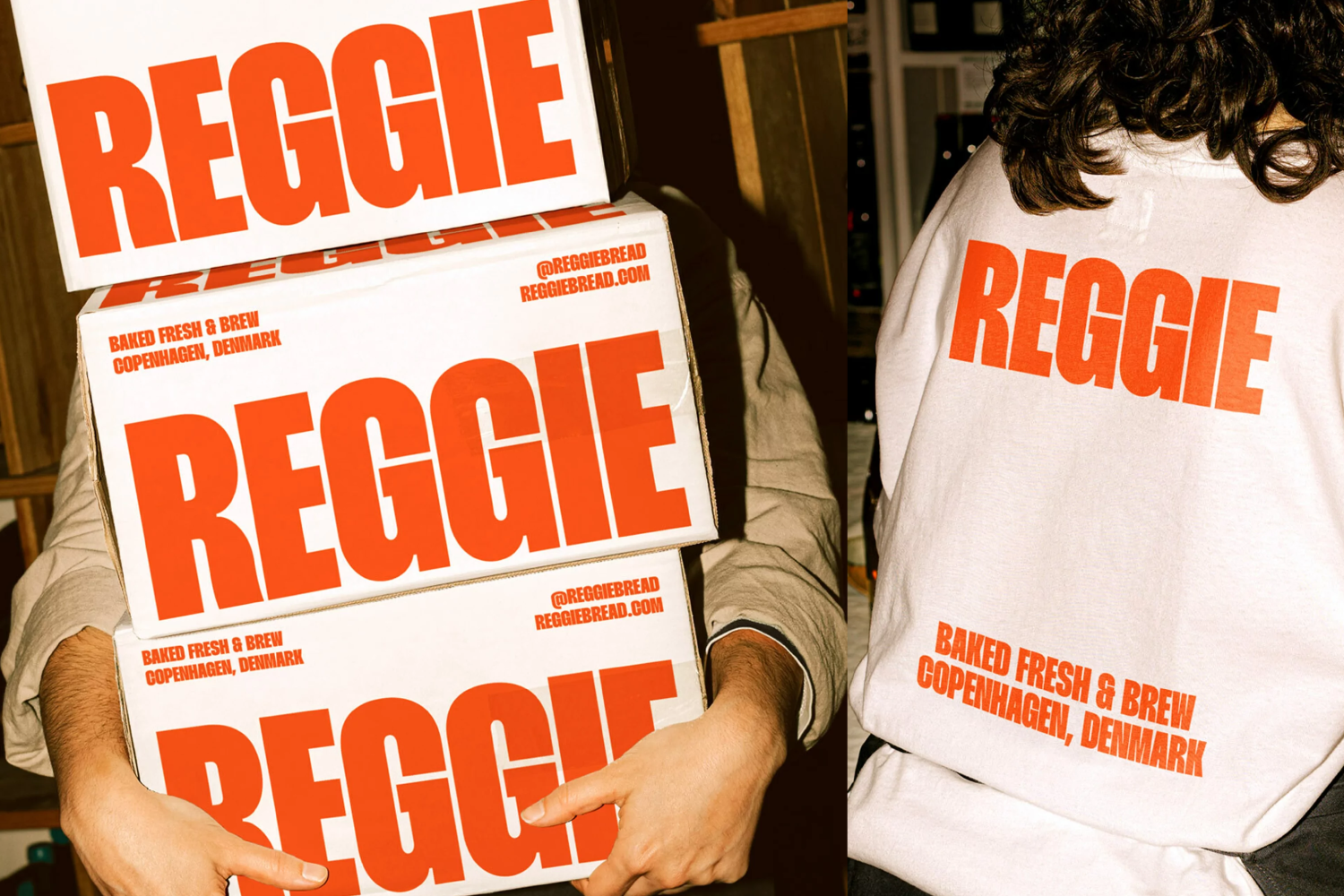
Cada época posee sus propias tendencias estéticas que la definen. Estas tendencias no germinan por generación espontánea. Se manifiestan por la confluencia de una serie de factores entre los que destacan principalmente los avances técnicos que las hacen posibles y las realidades sociales, políticas, económicas y culturales que les dan forma y profundidad.
Si analizamos el presente bajo este prisma, nos daremos cuenta enseguida de que la aceleración de los avances tecnológicos —con la IA a la cabeza— están provocando una auténtica revolución visual. A su vez, desde que comenzó el siglo XXI estamos inmersos en una convulsa actualidad sociopolítica mundial que, grosso modo, lo está poniendo todo patas arriba, y que, lejos de amainar, cada día parece ir a más. Ambas circunstancias interactúan y se retroalimentan; son causa y a la vez efecto la una de la otra.
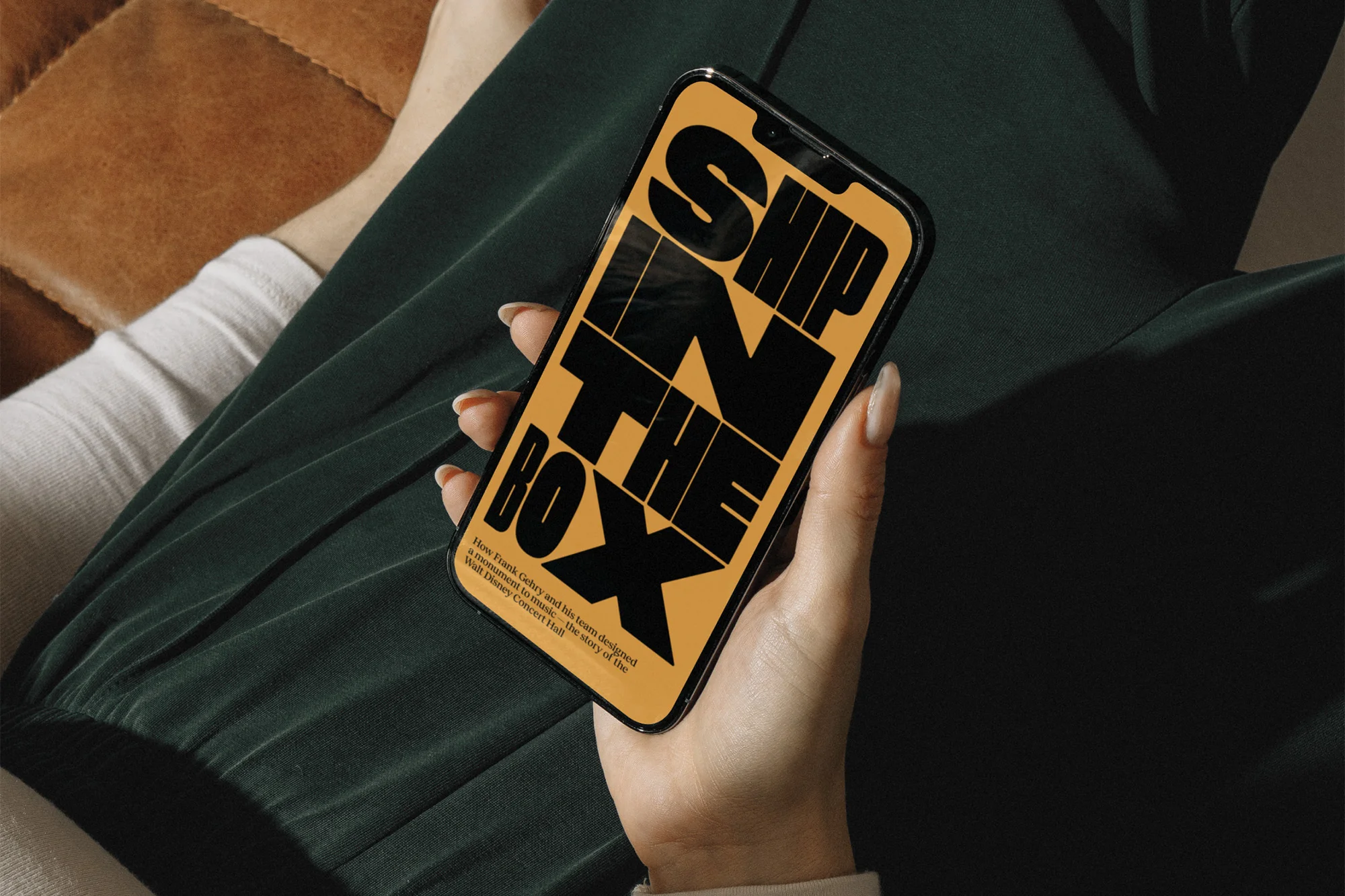
¿Y qué nos dice la tipografía de todo esto?
El diseño gráfico y la tipografía —y el universo de la cultura visual en general— son un reflejo del mundo en el que surgen y en este agitado y salvaje mundo de 2024 es imposible, a mi juicio, destacar una tendencia por encima de las demás, posiblemente como consecuencia de la agitación social. Llevamos años haciendo estos ejercicios de recapitulación y después de este tiempo es posible concluir que la tendencia tipográfica predominante es que no hay tendencia tipográfica predominante.
A lo largo de este artículo, vamos a repasar algunas tendencias, corrientes o movimientos tipográficos que nos parecen significativos y que, bajo nuestro punto de vista, son los que marcan el presente. Como hemos dicho en alguna ocasión anterior, no tenemos afán de exhaustividad, sino que lo que pretendemos no es más que esbozar un retrato tipográfico personal de la actualidad, tal vez como excusa para hacer algo que adoramos: hablar de tipografía.
Tipografías invertebradas
La tipografía solía tener esqueleto. Durante siglos ha sido sinónimo de solidez, de precisión arquitectónica. Pero ya no es así. Las dos dimensiones ya no son lo que eran. Las letras se vuelven blandas y flexibles, son como burbujas que se hinchan, incluso parece que se van a escapar de la pantalla. Lo que antes parecía anatema ahora se hace con descaro: las letras se deforman y no es difícil sospechar que en ello hay rebeldía y un decidido afán por dejar bien claro que, en realidad, no todo está inventado.
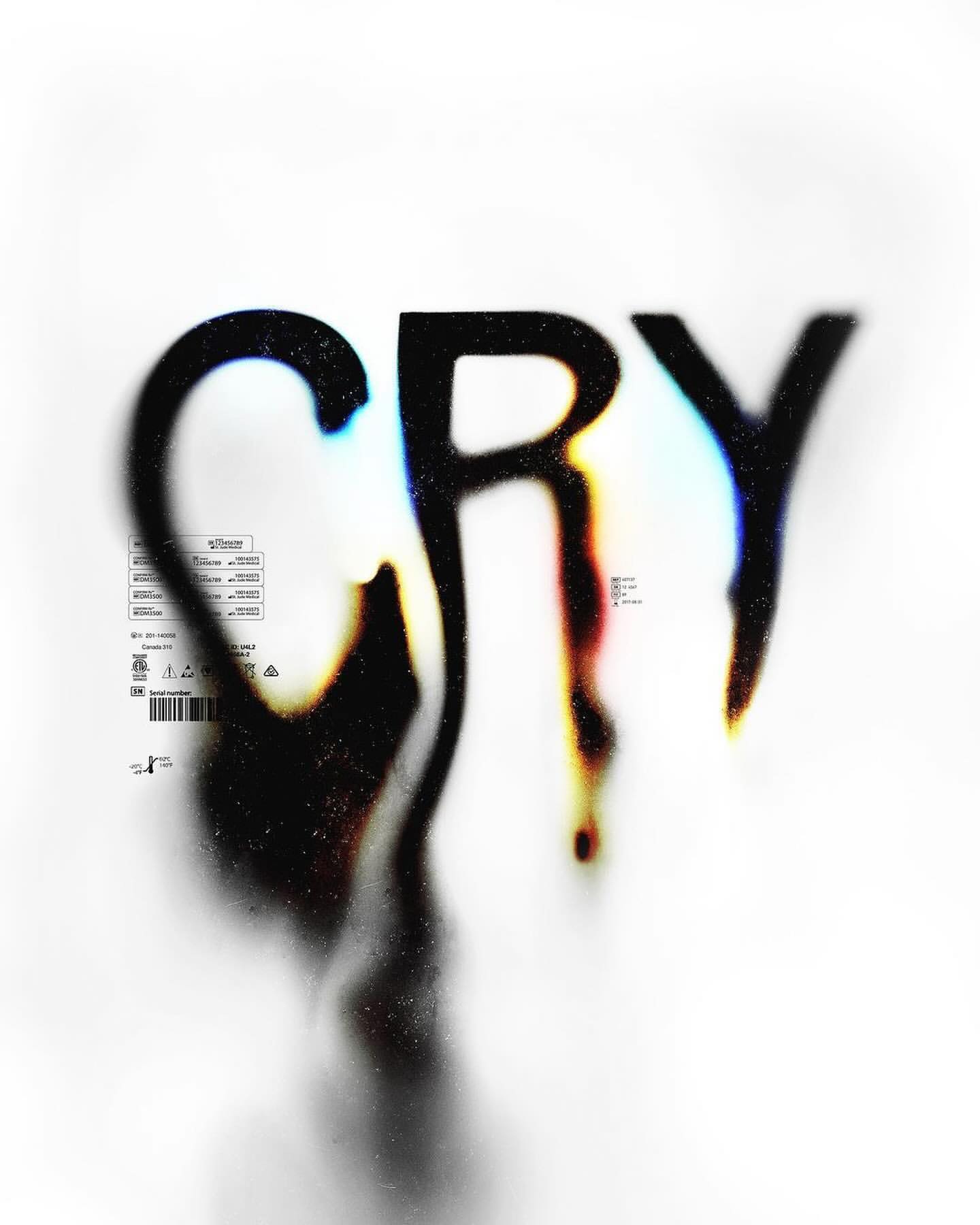
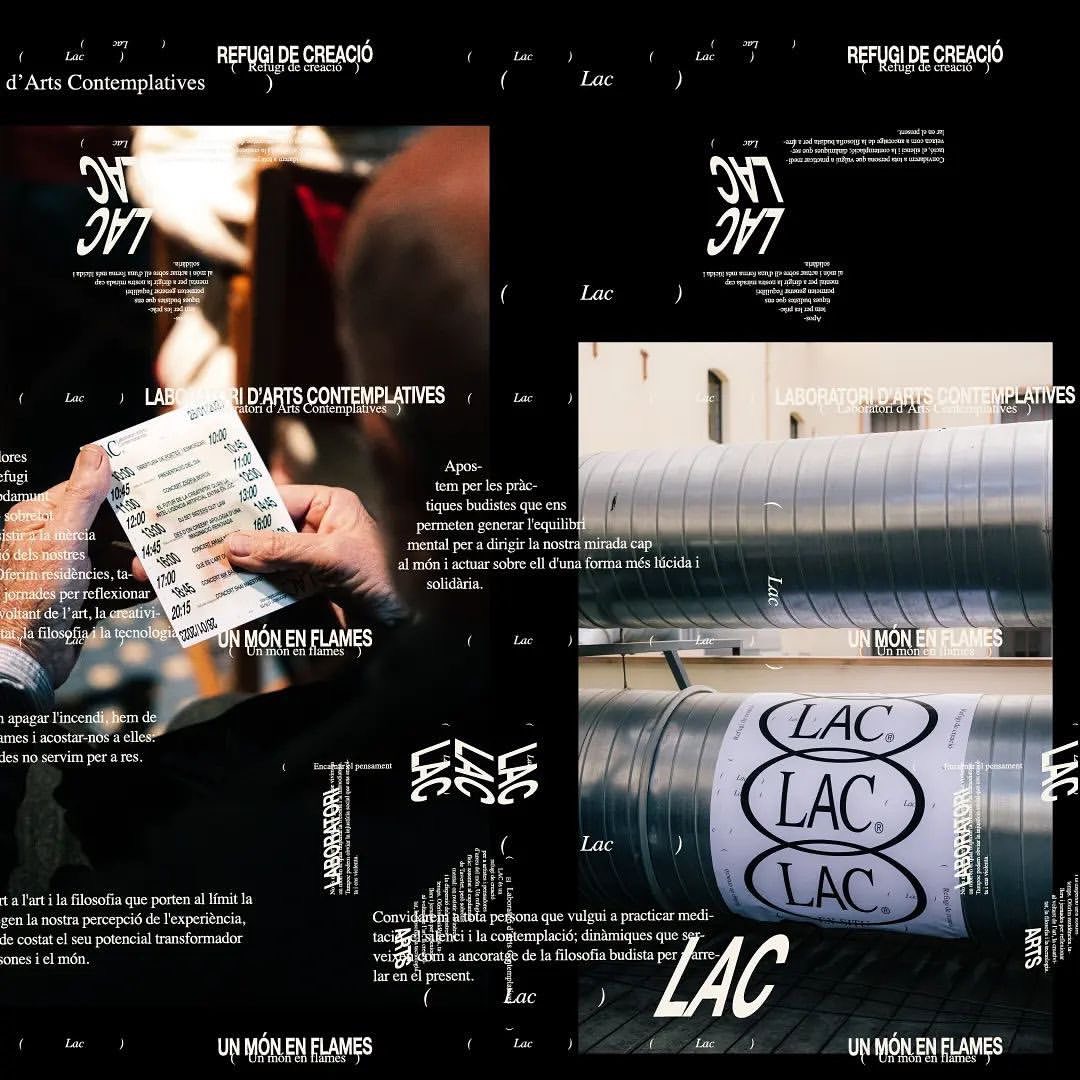
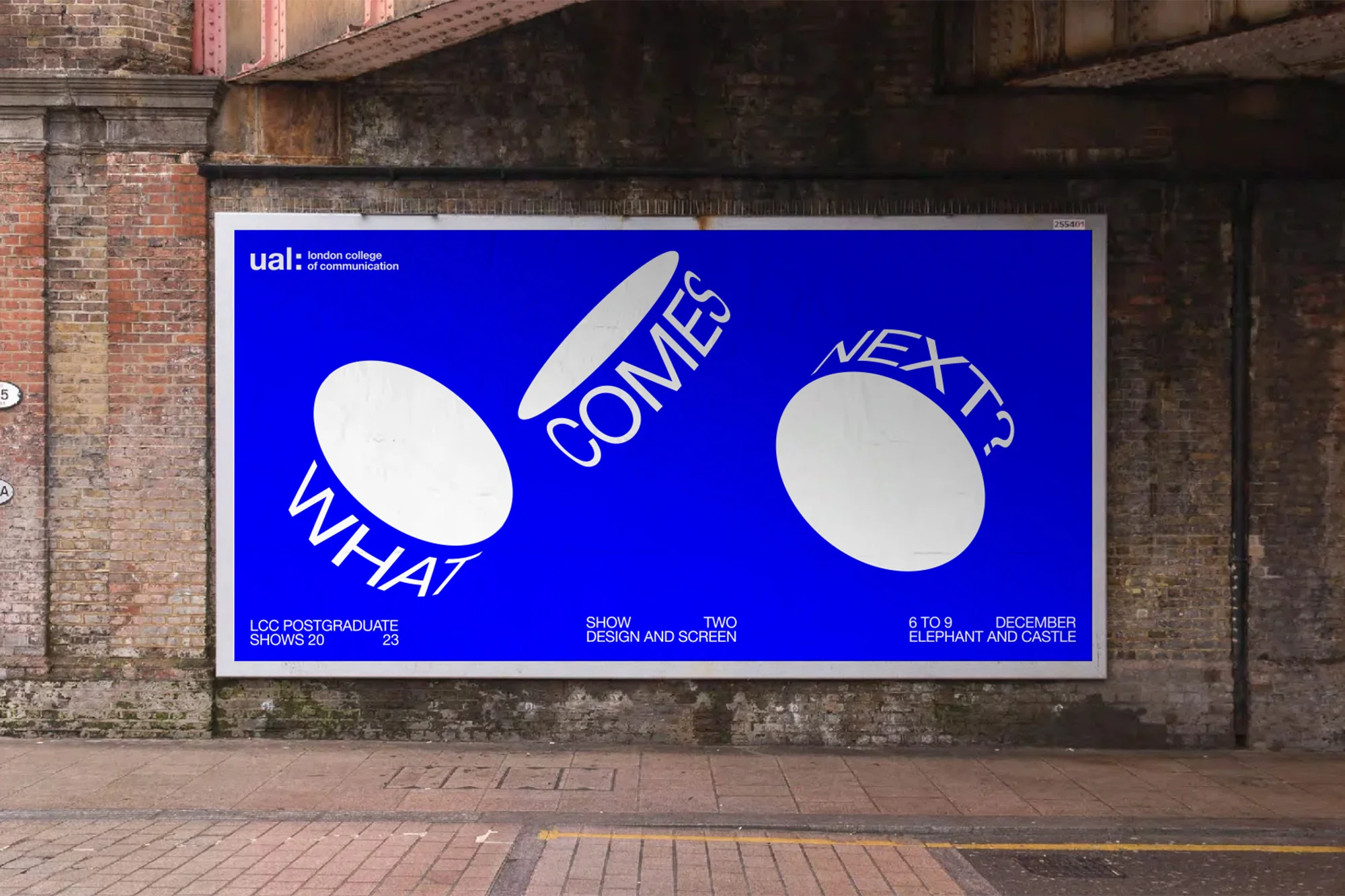
Más es más
Parece existir cierta inclinación por cubrir toda la superficie con letras. El tamaño sí es importante si de lo que se trata es de no pasar desapercibido. Hay cierta urgencia juvenil en estas tipografías sobredimensionadas, como si el mundo fuera demasiado pequeño para mi mensaje. Es esta una pulsión primitiva, y en cierto modo ingenua, lo que la hace irresistible. El tamaño como un valor estético en sí mismo, incluso como mensaje.
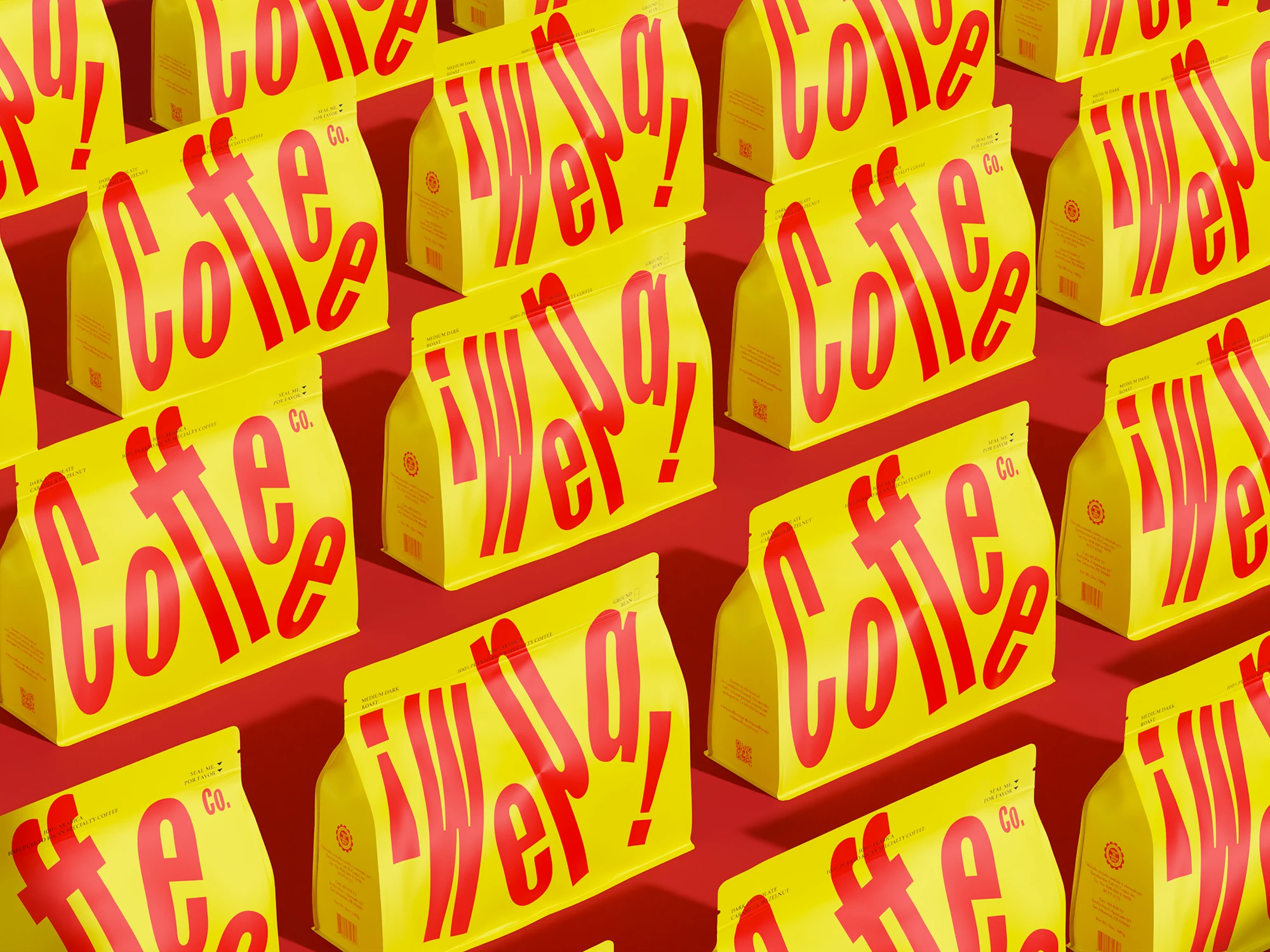
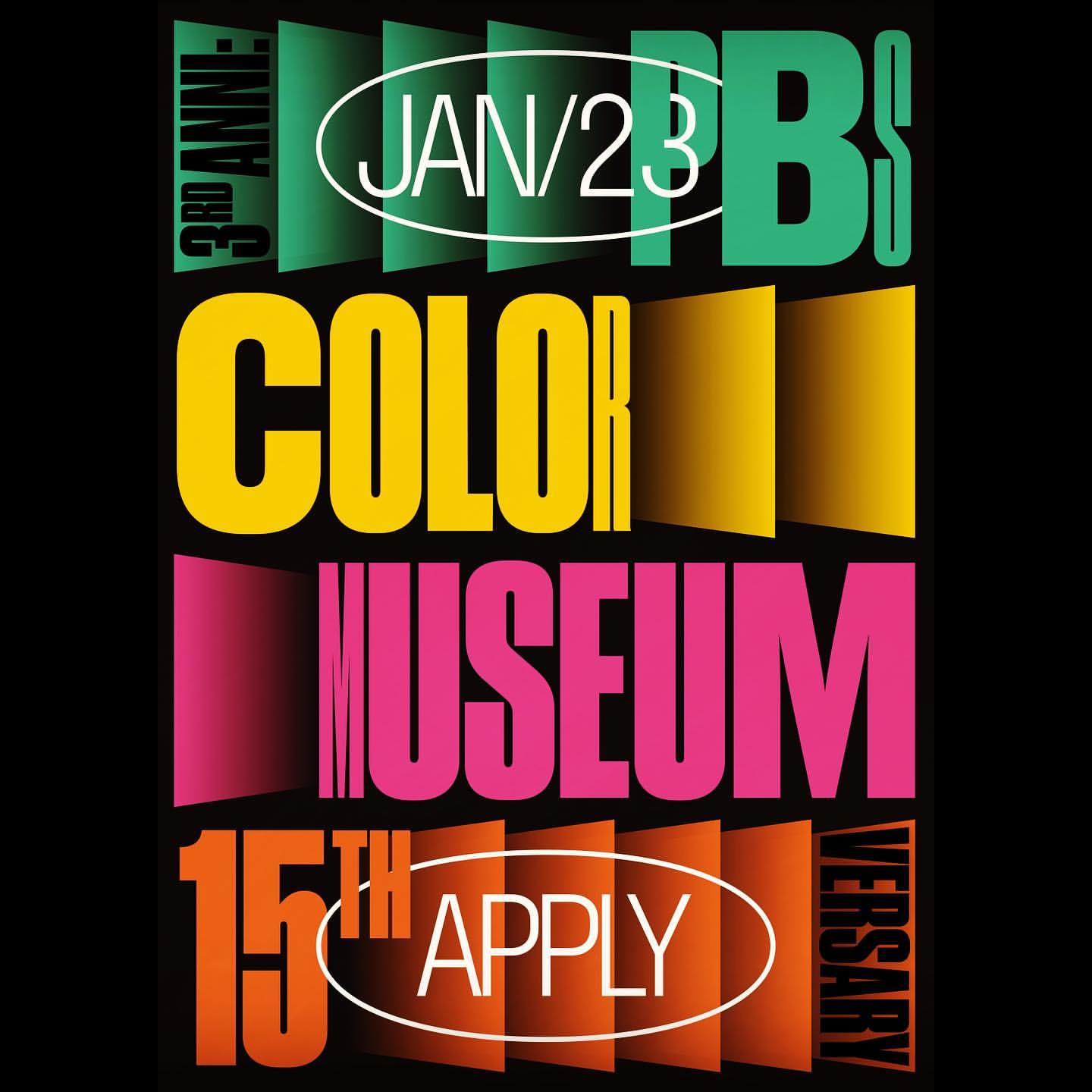
Expresionismo tipográfico
En un primer momento hablamos de experimentación. Pero pronto nos dimos cuenta que de lo que se trataba era de expresar emociones a través de la tipografía. Si todo es relativo, la legibilidad también podría serlo en ciertos contextos. El objeto letra es capaz de una inmensa expresividad formal por encima de cualquier otra consideración, reclamando para sí el estatus de artefacto (tipo)gráfico autónomo.
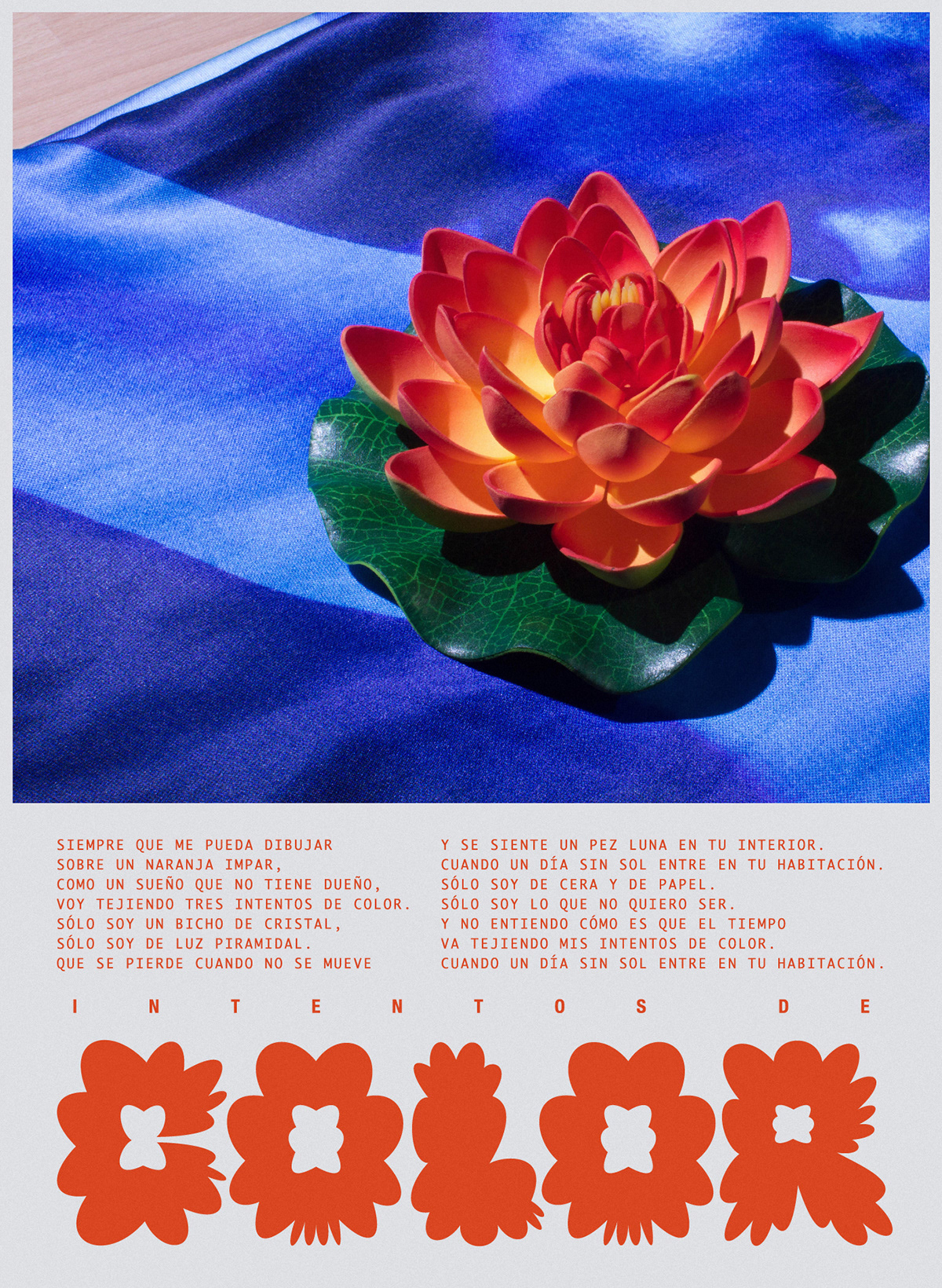
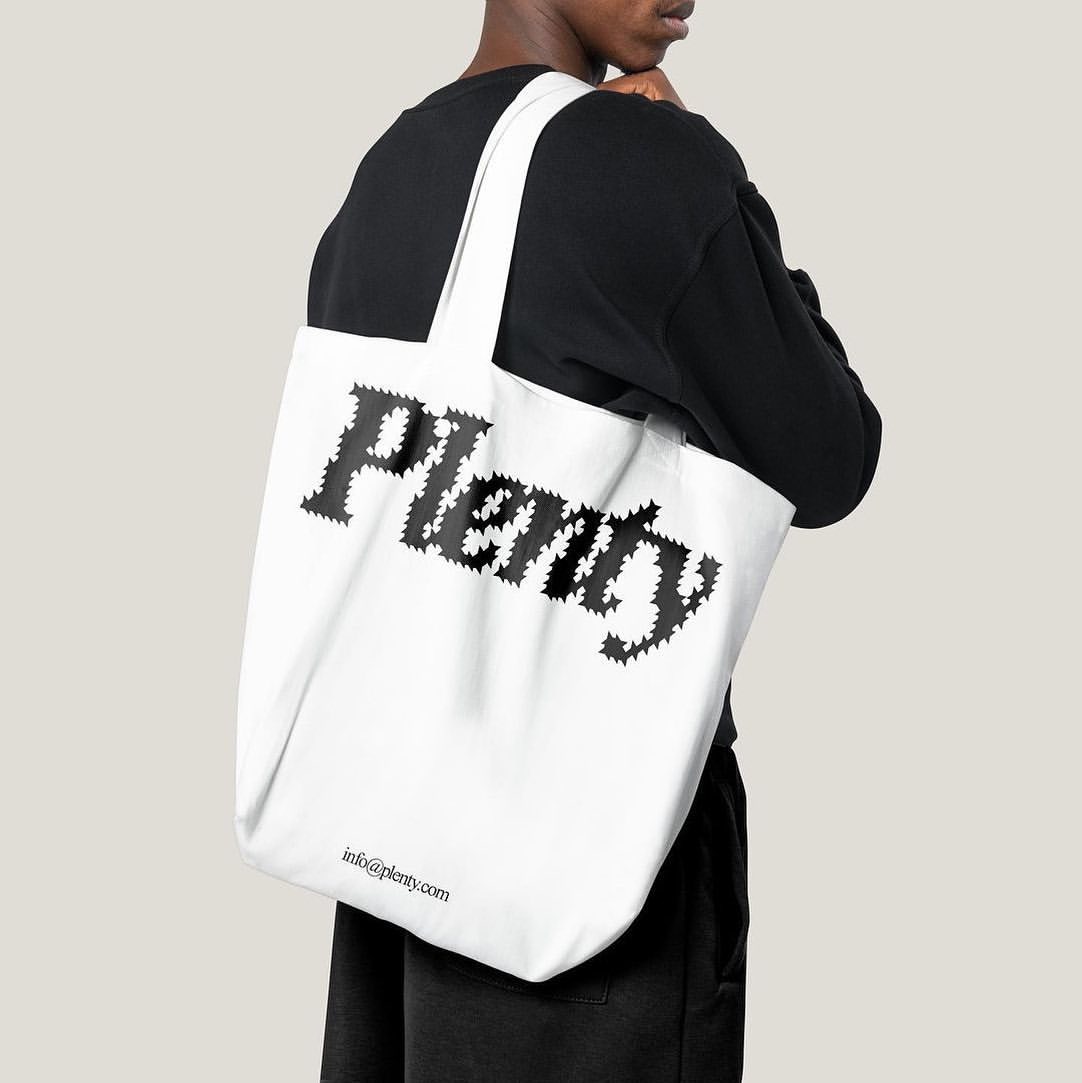
Grid
Observando algunas de la tendencias actuales llega a parecer incluso inverosímil, pero el diseño necesita una estructura subyacente. Porque no puede haber comunicación sin orden. El grid es una herramienta, quizás de las más útiles que existen, pero también puede dar un paso adelante y convertirse ella también en protagonista. No se trata de monoespaciadas, sino más bien de ordenar el espacio de un modo sistemático, aunque dentro de cada cuadrícula pueden suceder cosas inesperadas.
Anotaciones manuales
Sería legítimo afirmar que no hay belleza comparable a la producida por la imperfecta mano humana. Lo escrito a mano es un valor en sí mismo, ya se trate de lettering o de caligrafía. En el universo de la comunicación visual siempre habrá espacio para la impronta manual, incluso para esas letras casuales e ingenuas de las notas escritas a vuelapluma, casi sin mirar, que pueden erigirse también en un estilo en sí mismo.
Ya no existe lo retro
Hemos hablado un poco más arriba de la relatividad de la legibilidad. Sin embargo, si hay algo verdaderamente relativo en el universo tipográfico en el siglo XXI es lo retro. Lo retro ha dejado de existir, afortunadamente. Además, en tiempos inestables y agitados como los actuales, es natural acudir a lo que «siempre» ha funcionado, como si se tratara de buscar refugio o, más bien, de que el suelo no se mueva.